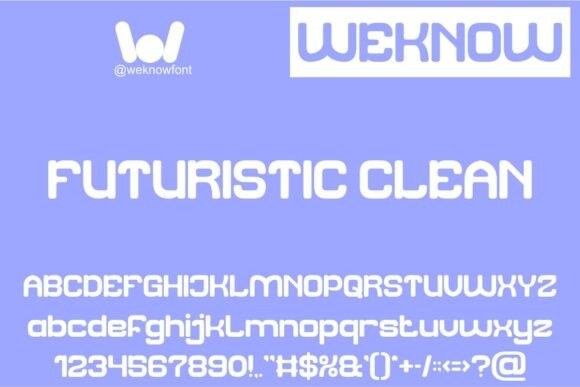
Futuristic Clean
Encontrar los elementos de diseño adecuados puede ser un desafío, pero Futuristic Clean ofrece una colección excepcional que eleva tu trabajo al instante.
Elaborado con precisión, Futuristic Clean proporciona vectores limpios, tipografía suave y una licencia comercial para tu tranquilidad.